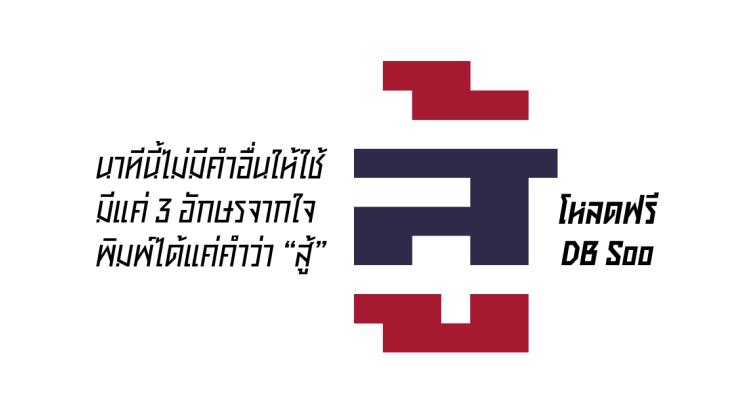
DB Soo
นาทีนี้ไม่มีคำอื่นให้ใช้
มีแค่ 3 อักษรจากใจ
พิมพ์ได้แค่คำว่า “สู้”
DB ChatGen
ยุคสมัยที่คนทุกวัยล้วนร่วมอยู่ใน 'Chat Generation' นั้น หน้าจอสื่อสารเล็กลง ตรงข้ามกับปริมาณข้อมูลท่วมท้น เป็นผลให้ต้องใส่ใจความ 'ชัดเจน' ของฟอนต์ที่ใช้อ่านมากขึ้น.
DB Uniwidthai
เลือกเปลี่ยนน้ำหนักฟอนต์
โดยไม่สะเทือน layout
CW Thainese
ฟ อ น ต์ ที่ ไ ม่ ไ ด้ มี
แ ค่ เ ส้ น ห มึ ก !
DB Manoptica
คืองานอนุรักษ์แบบอักษรประดิษฐ์ ที่ถือเป็นต้นแบบของการนำตัวอักษรฝรั่งมาดัดแปลงเป็นไทย.
DB Soda
เป็นฟอนต์ตัวพื้นไทยที่เป็นสัญลักษณ์ของการก้าวสู่ยุคตัวพิมพ์ดิจิทอลแบบ OpenType ของไทย
DB ThaiText
เป็นฟอนต์ตัวพื้นยุค PostScript ของไทยที่พัฒนามาจากแบบตัวพิมพ์โมโนไทพ์กลาง
DB NopPana
เป็นฟอนต์ดิสเพลย์ไทยหัวกลม ตัวกว้าง ที่สร้างมาจากแบบอักษรขูด มานพ 9
DB NopIntanon
เป็นหนึ่งในแบบอักษรขูด ชุด ‘มานพ’ ที่อนุรักษ์เป็นฟอนต์ OpenType โดยได้รับสิทธิ์จากผู้ออกแบบในการปรับปรุงพัฒนาเชิงพาณิชย์ร่วมกัน